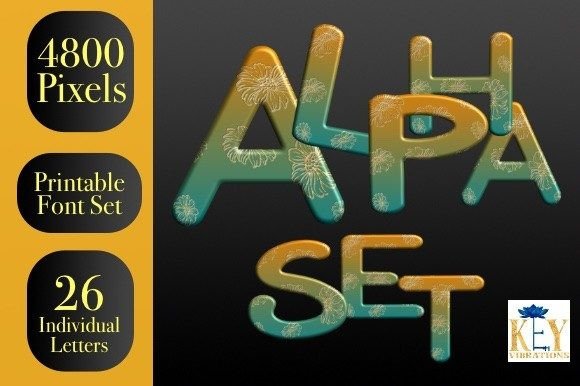
3D Sunflower Sunset Alpha Set Printable
قد يكون العثور على عناصر التصميم المناسبة أمرًا صعبًا، ولكن 3D Sunflower Sunset Alpha Set Printable يقدم مجموعة استثنائية ترتقي بعملك على الفور.
سواء كنت تقوم بإنشاء منتجات الطباعة عند الطلب أو دعوات الزفاف أو رسومات وسائل التواصل الاجتماعي، فإن 3D Sunflower Sunset Alpha Set Printable هو الخيار المثالي.